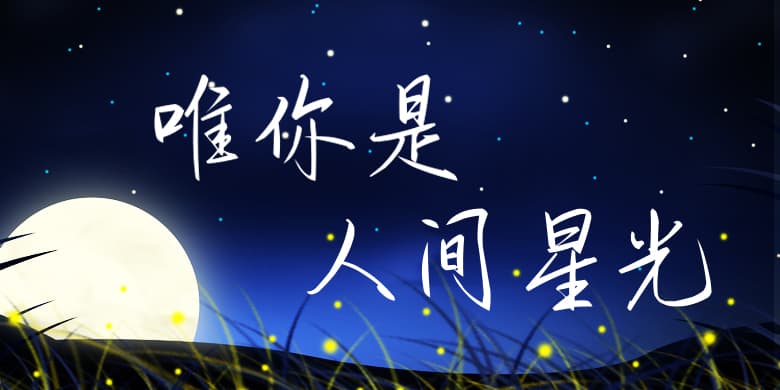
品牌:方正手迹设计师:刘殿儒发行时间:2019字库编码:大陆简体(GB2312-80)分类:常规书写·硬笔字体属性:精品字
如利剑般出鞘时剑光一闪,如雨燕般飞掠水面时自在从容,如琴键般起落时韵律和谐。这是该字体所传达出的一些内在气质。简洁明快的线条,粗细自然搭配,充满现代气息。结字方式继承传统,很好地结合了传统与现代。适用于现代诗歌、短文的排版以及文化、商业类品牌的广告语设计。